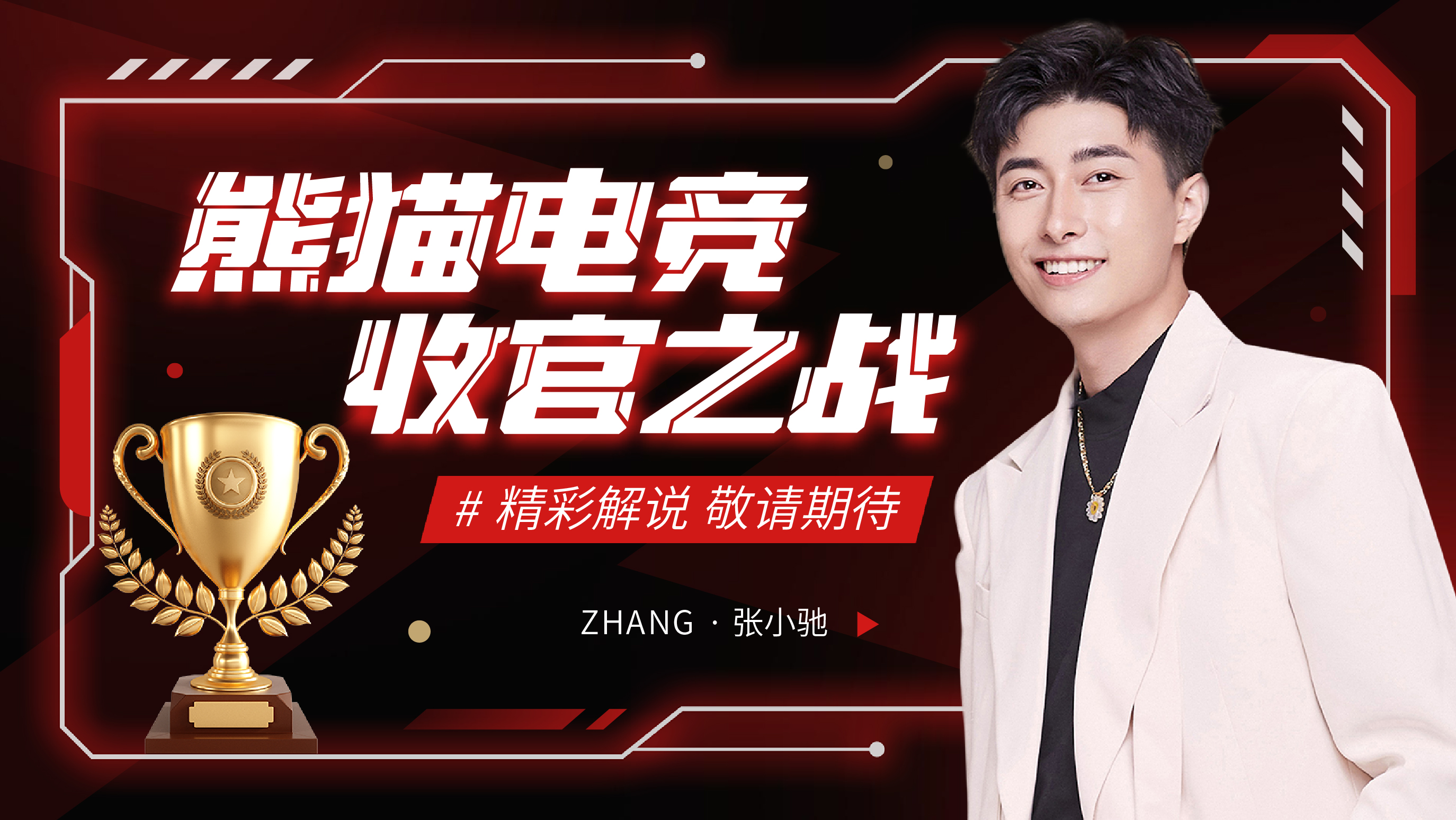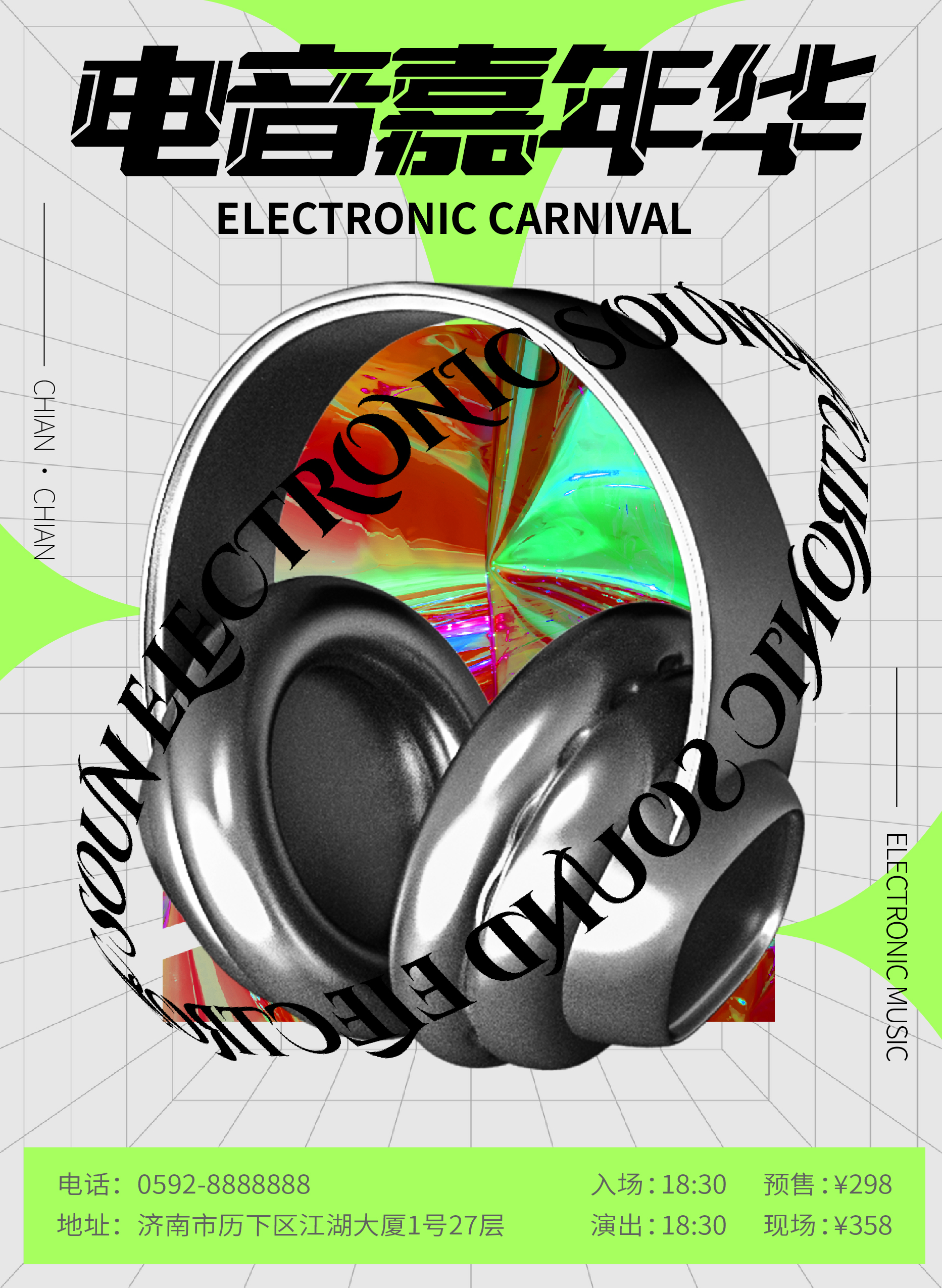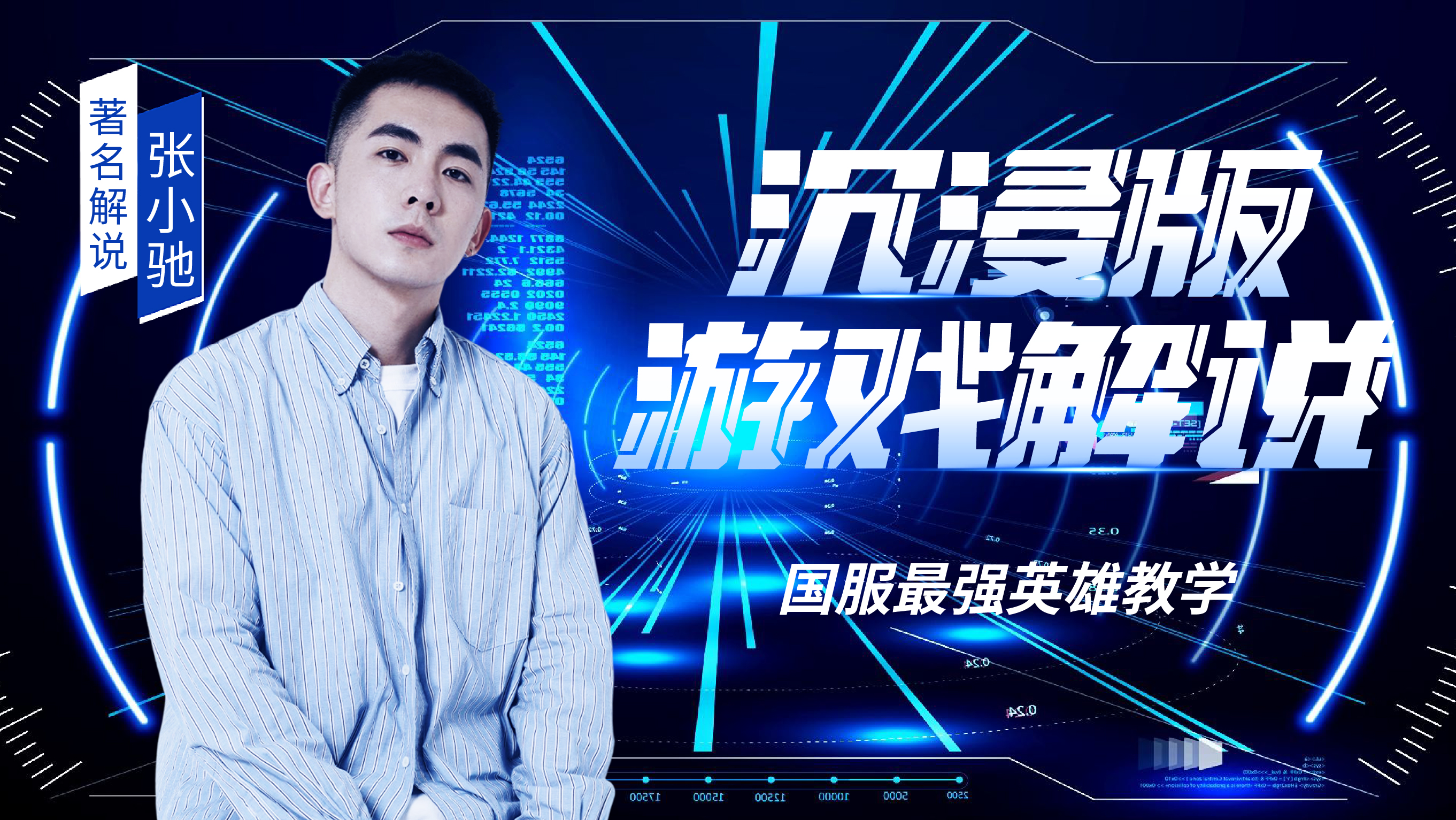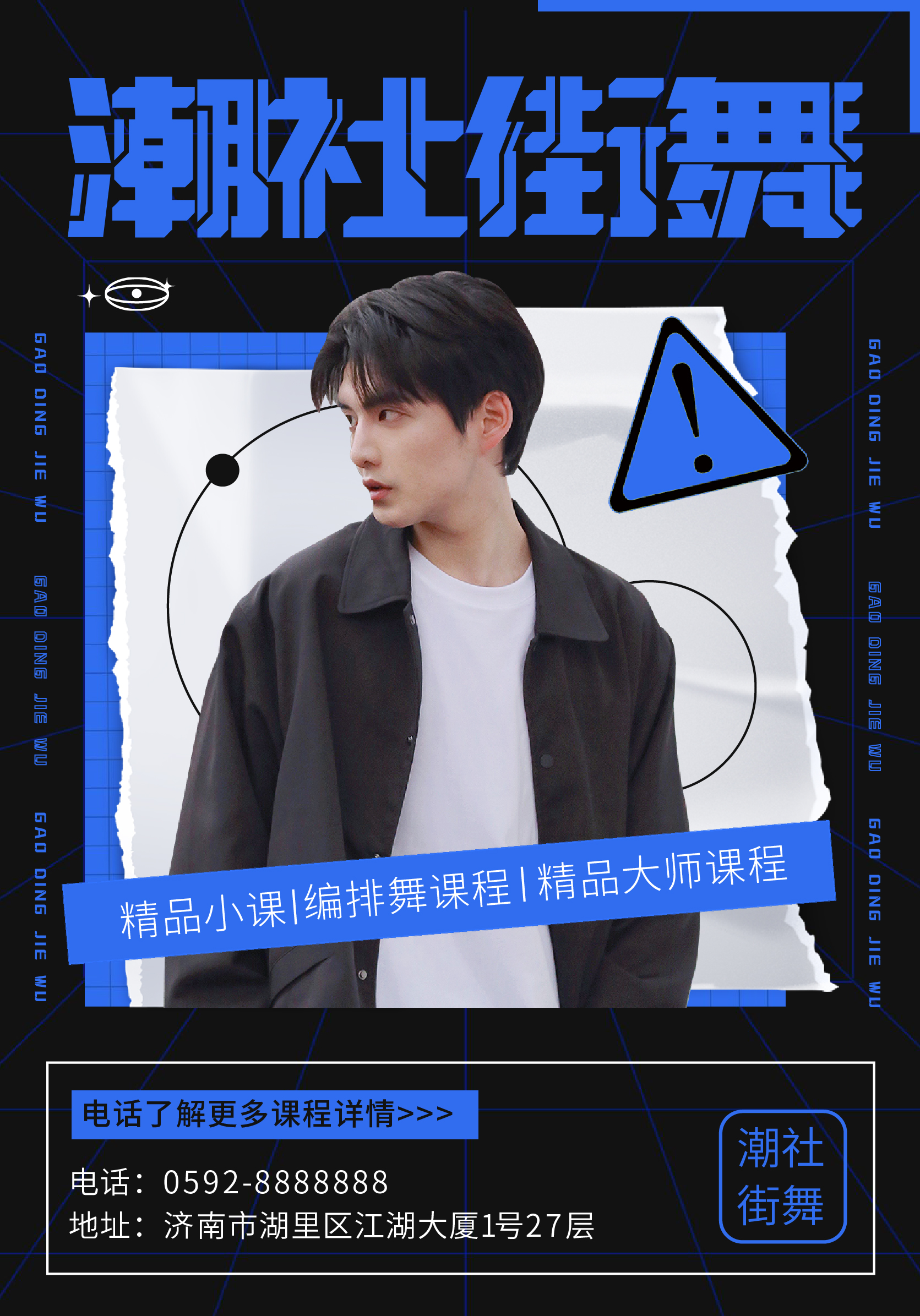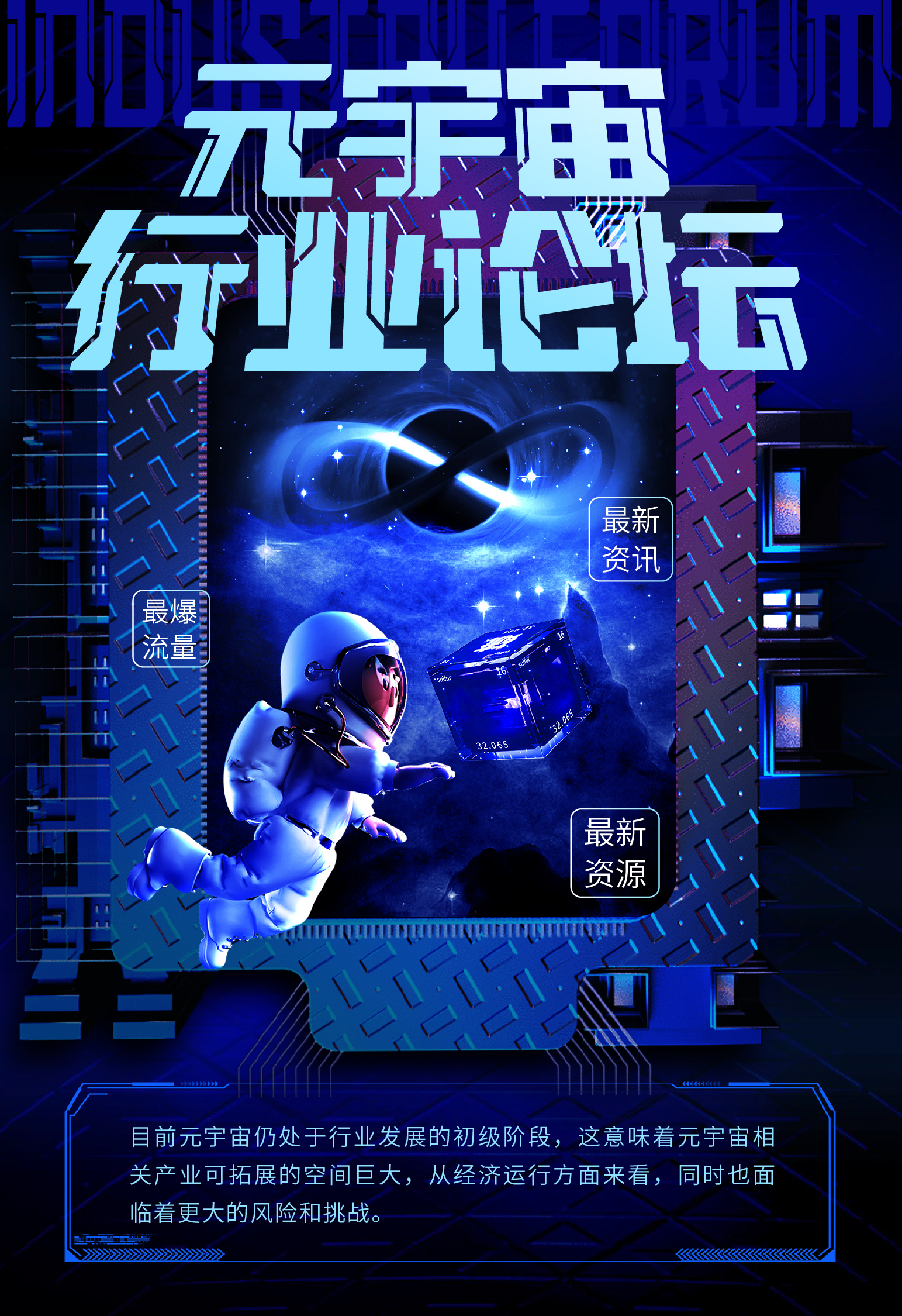
兵克战甲体
兵克战甲体,兵克战甲体,是一款富有科技感、机械感和力量感的创意字体,整体风格硬朗且充满力量感。该字体笔画加入了分明的机械线条和丰富的细节设计,不仅增强了字体的形式感,也使得字体在视觉上更具层次感和立体感。兵克战甲体凭借其独特的风格和强大的视觉冲击力,无论是在游戏动漫、动作科幻类电影还是广告包装等领域中,它都能够为作品增添无限的魅力和价值。
兵克战甲体字体介绍